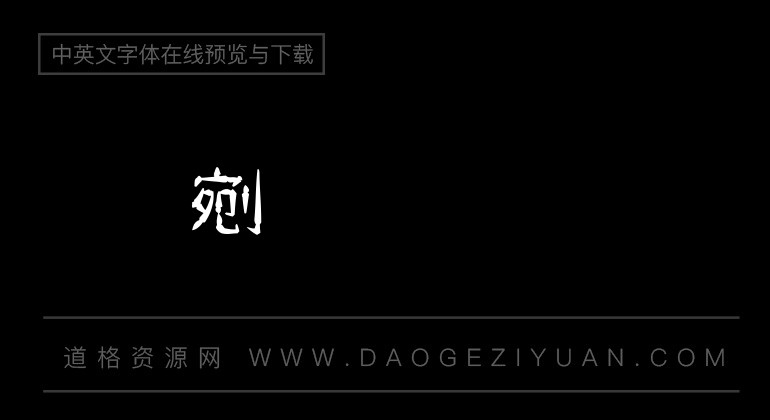
金梅鸦嘴笔字范例
金梅鸦嘴笔字范例是一种传统的汉字书法风格,它的特点是笔画细腻,笔画曲折,笔画间有节奏感,字体结构精细,笔画粗细有致。金梅鸦嘴笔字范例中,笔画要求有规律,细节要求有规矩,字体要求有灵动,笔画要求有灵活。金梅鸦嘴笔字范例的字体特征是:笔画细腻,笔画曲折,笔画间有节奏感,字体结构精细,笔画粗细有致。
金梅鸦嘴笔字范例是一款非常不错的手写艺术字体,具有很好的视觉感,适合于文化类的宣传设计、商业类品牌的广告和产品包装设计以及个性化文字排版等较多场景。